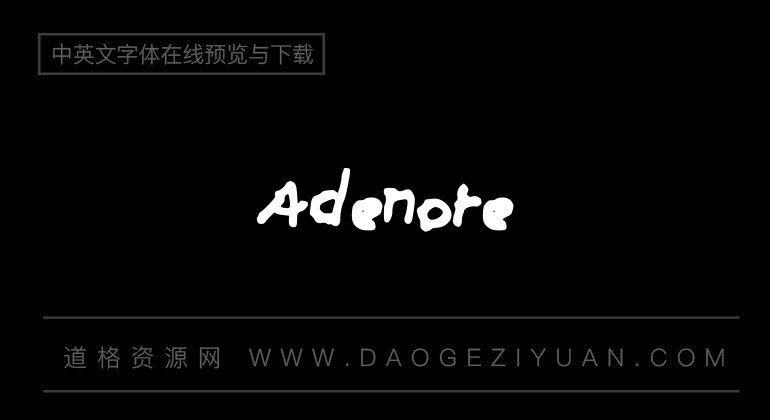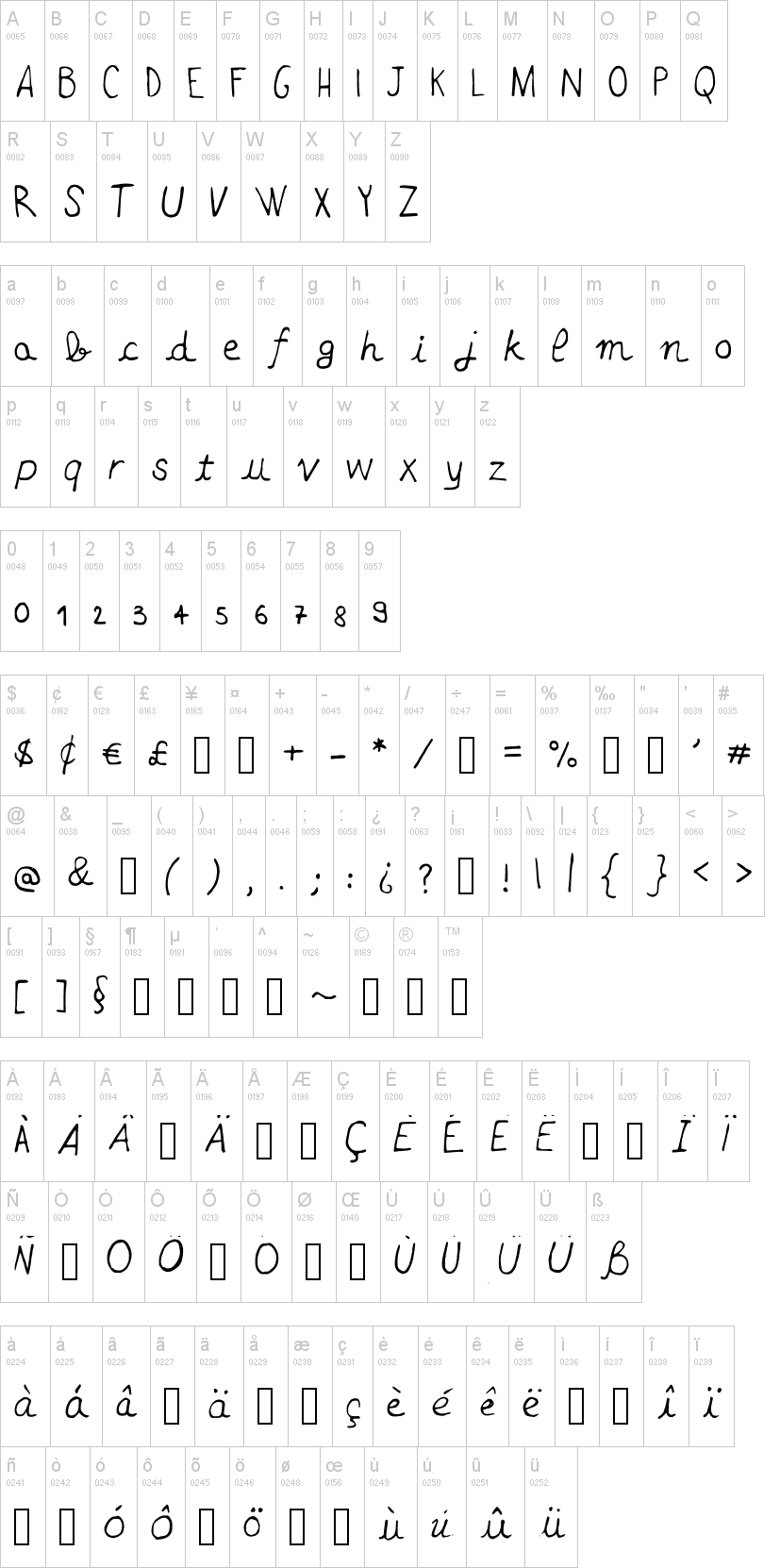
Adenote
? Adenote 字体是一款由 Fontfabric 创作的多功能字体,它具有独特的设计和视觉效果,适用于多种类型的设计项目,从标题到小型文本,从矢量图到印刷品,都能找到它的应用。它的设计充满活力,可以帮助你创建出独一无二的设计作品。它的多功能特性使其成为设计师们最爱的字体之一,因为它可以创造出更多样化的设计效果。
Adenote是一款非常不错的手写艺术字体,具有很好的视觉感,适合于文化类的宣传设计、商业类品牌的广告和产品包装设计以及个性化文字排版等较多场景。
Adenote字符映射图